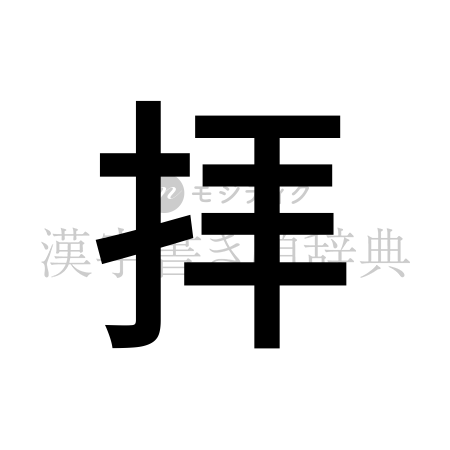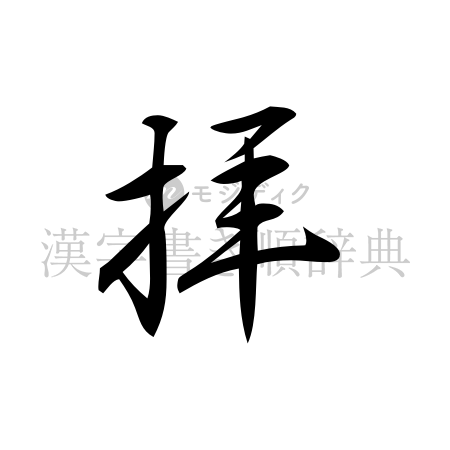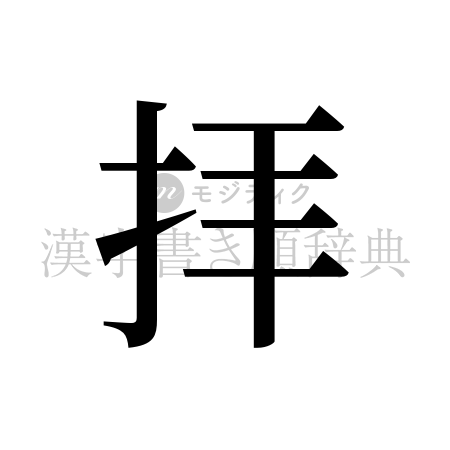
漢字「拝」(ハイ)の書き順・読み方・意味・部首・画数
「拝」の意味
- 敬意を表して礼をすること。
- 神仏や目上の人に対して、謹んで願いや感謝を表すこと。
- 「拝見」「拝聴」などの形で、謙譲の意を表す。
- 手紙などで、相手に敬意を表すために用いる語。
漢字は1文字で多様な意味を持ちますが、「拝」を英語で表す場合、一般的には worship, adore, pray to などがあります。
「拝」の成り立ち・由来
| 構造 | 手(両手)+下げるさま=手を下げて礼をする |
「拝」の旧字体は「拜」で、手を表す部分を重ね、両手を下げて敬意を示すさまを表した会意文字とされます。頭を下げ、手を合わせて神仏や目上の人にひざまずいて礼をする動作から、「おがむ」「うやまう」の意味が生まれました。そこから「拝見」「拝聴」のように、自らをへりくだって相手を敬う謙譲の語にも広く用いられます。旧字「拜」の右側が簡略化され、現在の「拝」の字形となりました。字源には諸説があります。
※ 右側の構成要素の解釈をめぐって字源には諸説があります。
「拝」を含む熟語・単語とその意味
- 拝礼 - はいらい
- 朝廷や院における元旦の拝賀。
- 拝殿 - はいでん
- 神社で、礼拝が行われる殿舎。
- 参拝 - さんぱい
- 神社に行って拝むこと。寺にもいう。